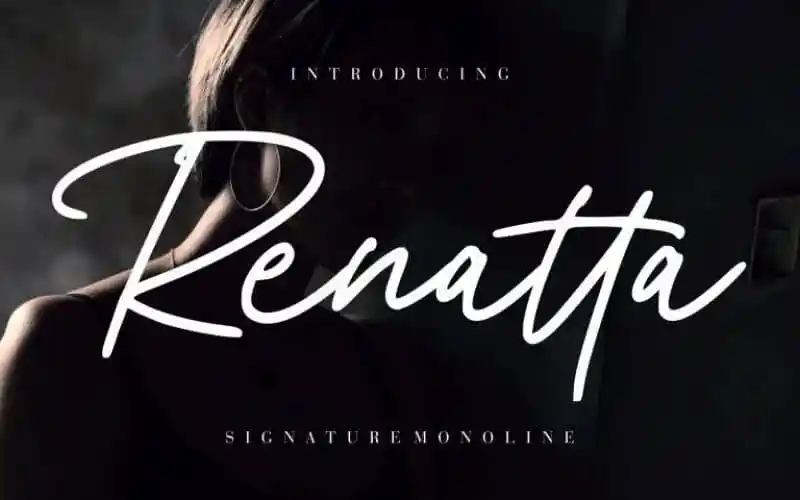
Renatta Handwritten Font – Download Grátis
A Renatta Handwritten Font é uma elegante tipografia feita para quem busca uma sensação romântica e delicada. Com letras arredondadas perfeitas, esse estilo único foi criado pela Creatype Studio e traz um toque de personalidade que torna qualquer projeto mais especial. Perfeita tanto para projetos de marca como para designs de casamento, redes sociais ou anúncios, esta fonte também é ótima para embalagens de produtos, design do produto, etiquetas, fotografias e até mesmo marcas. A Renatta enriquece seu trabalho com um toque de escrita a mão que se adapta a diversos tipos de projetos, seja em cartões de convite ou material de papelaria. Uma fonte tão única como esta é perfeita para quem busca uma paixão e delicadeza nos detalhes de seus trabalhos gráficos.